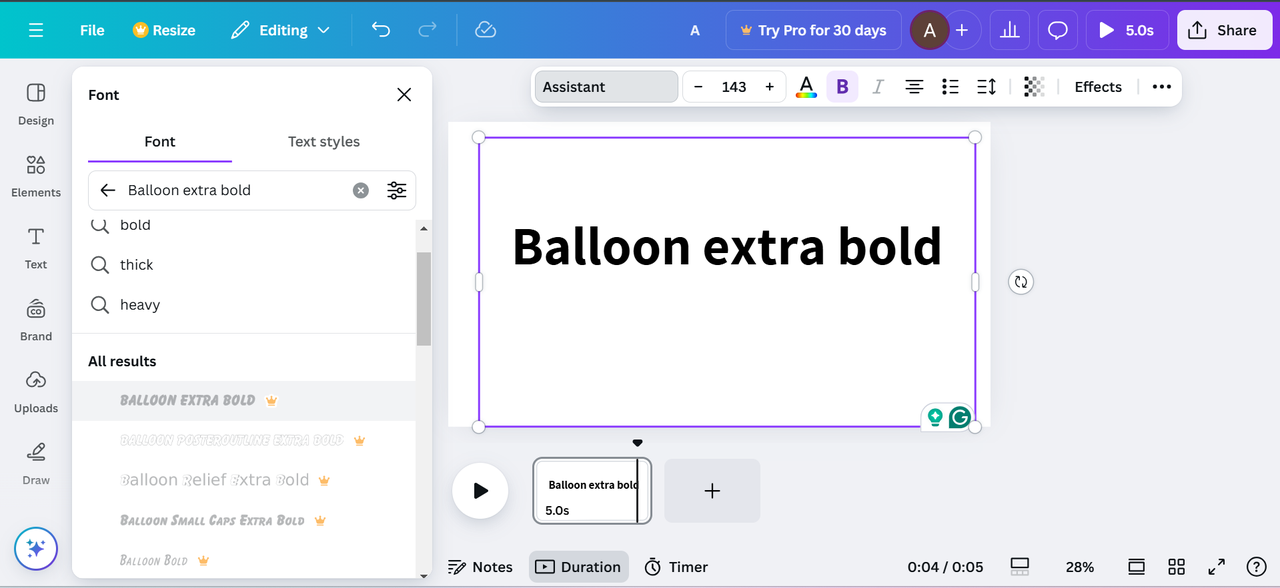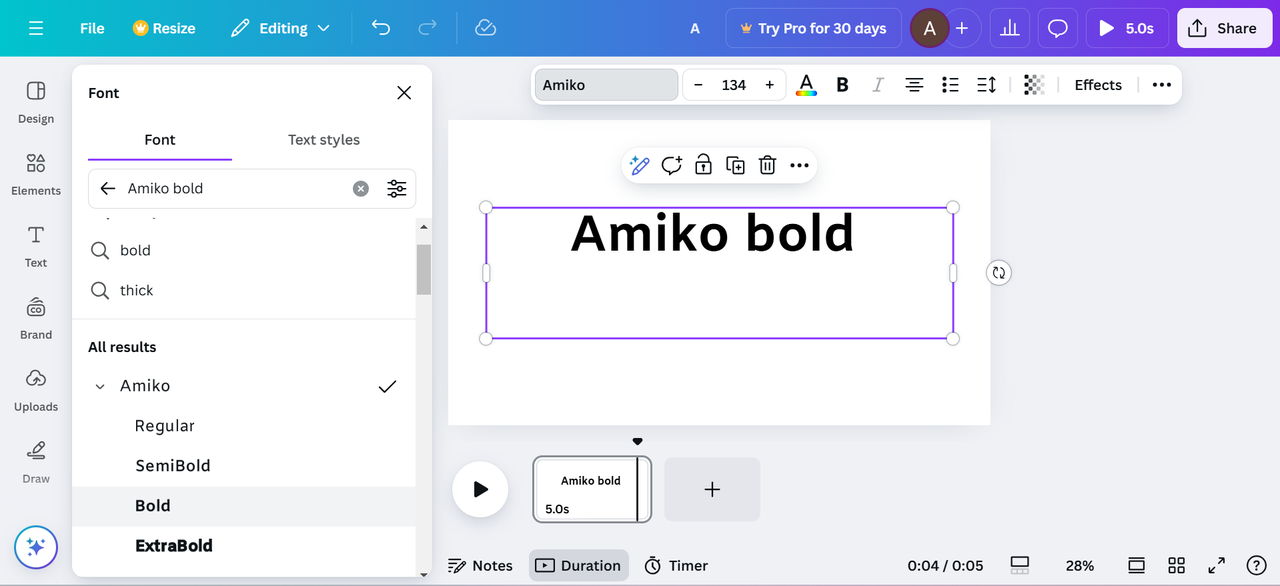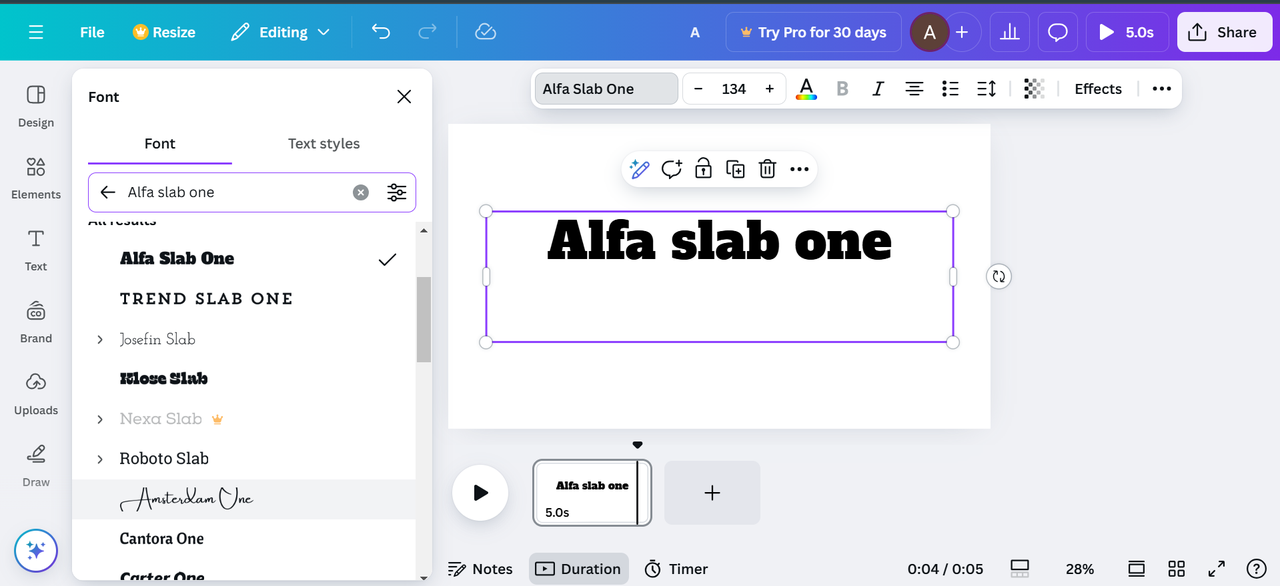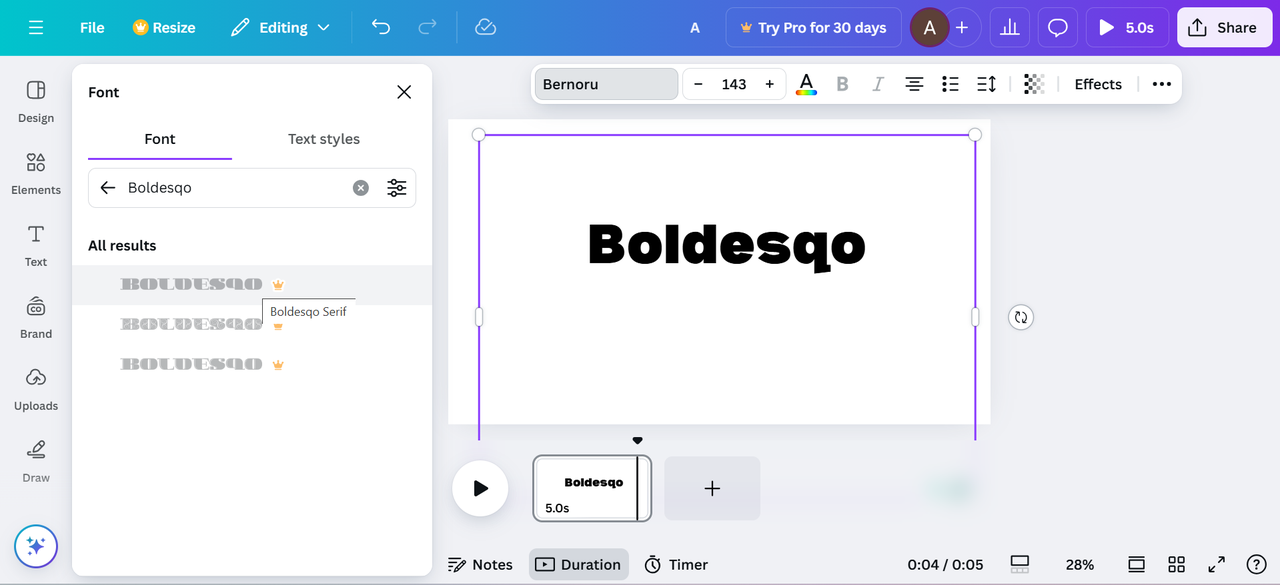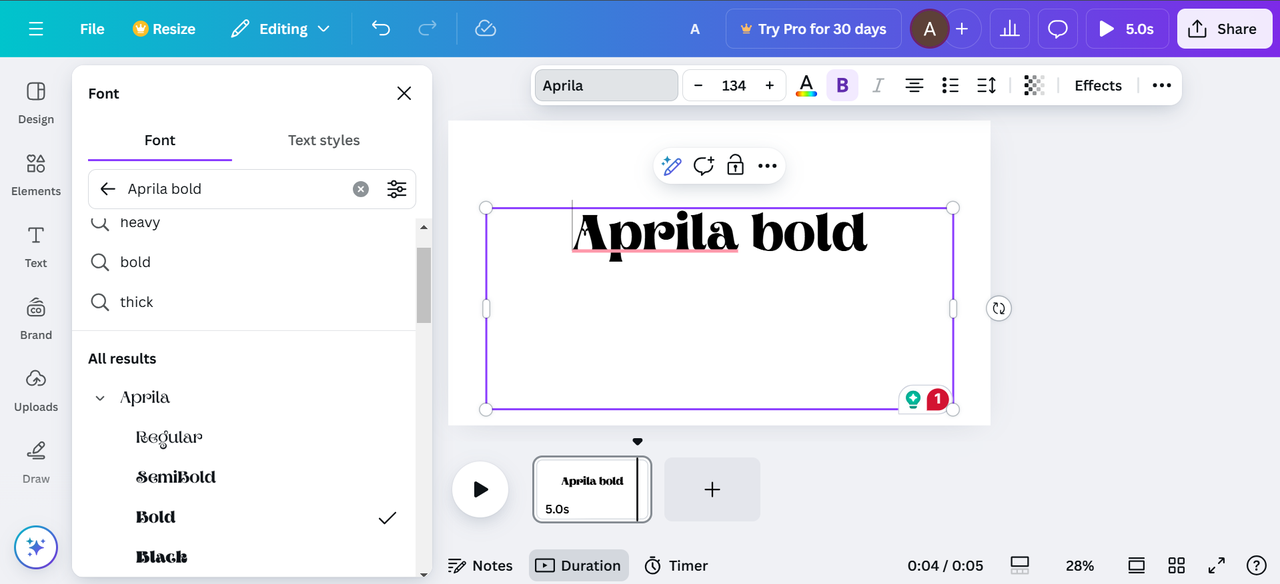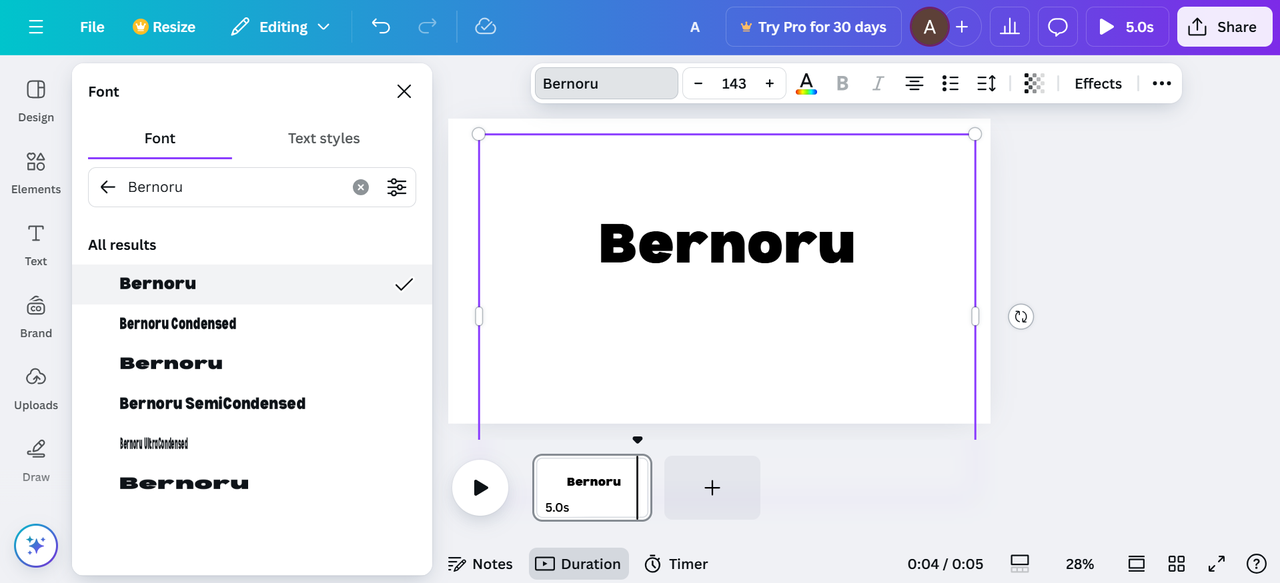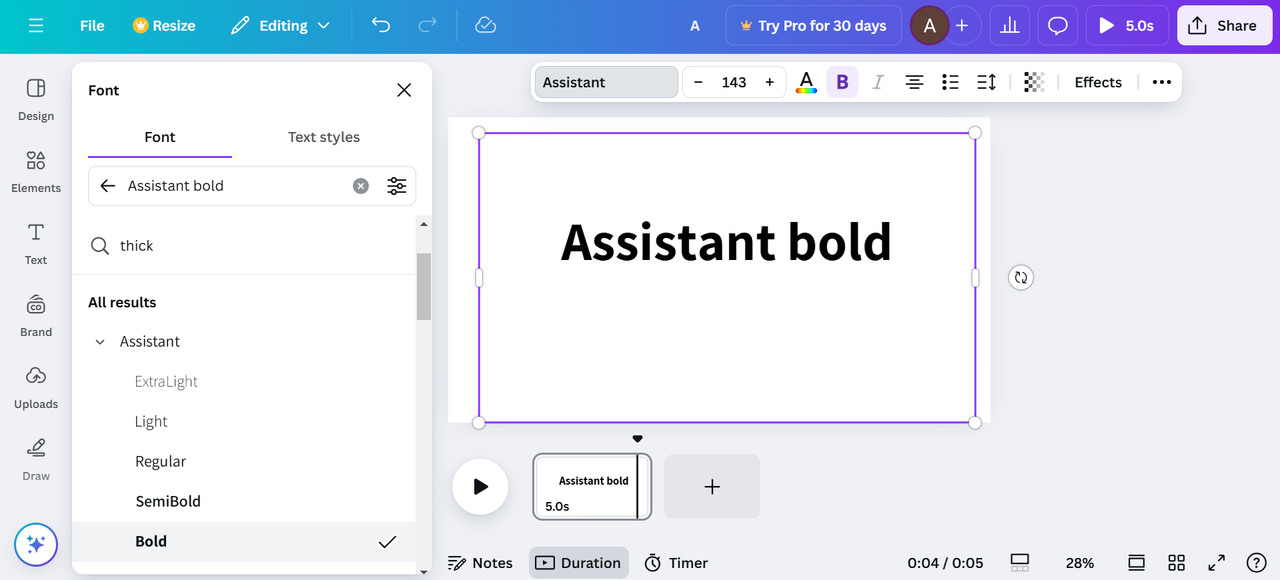
Εξερευνήστε 10 μοναδικές τολμηρές γραμματοσειρές στον Canva για δημιουργικά infographics
Εξερευνήστε τις καλύτερες τολμηρές γραμματοσειρές στο Canva για να κάνετε τα σχέδιά σας να ξεχωρίζουν. Ανυψώστε εύκολα τις αναρτήσεις κοινωνικών μέσων, τις παρουσιάσεις και τα υλικά μάρκετινγκ. Εναλλακτικά, χρησιμοποιήστε τον επεξεργαστή επιφάνειας εργασίας CapCut για να κάνετε έντονη γραφή και να αλλάξετε το μέγεθος του κειμένου σας σε βίντεο.
Το τολμηρό κείμενο είναι ένας ισχυρός τρόπος για να τραβήξετε την προσοχή και να τονίσετε τα βασικά σημεία σε οποιοδήποτε σχεδιασμό, ειδικά στα infographics όπου η σαφής επικοινωνία είναι απαραίτητη. Η Canva, μια ευέλικτη πλατφόρμα σχεδιασμού, παρέχει μια σειρά από μοναδικές, τολμηρές γραμματοσειρές που διευκολύνουν τη δημιουργία εντυπωσιακών οπτικών. Σε αυτό το άρθρο, θα διερευνήσουμε 10 ξεχωριστές τολμηρές γραμματοσειρές στο Canva που είναι ιδανικές για την αποτελεσματική μετάδοση του μηνύματός σας.
Δώστε τολμηρές εντυπώσεις με τις καλύτερες τολμηρές γραμματοσειρές στο Canva
Αν θέλετε το κείμενό σας να αφήσει μια μόνιμη εντύπωση, η επιλογή των τολμηρών γραμματοσειρών της Canva είναι το τέλειο εργαλείο. Από καθαρά, μοντέρνα σχέδια έως κλασικές, τολμηρές γραμματοσειρές serif, η Canva σας βοηθά να δώσετε έμφαση και προσωπικότητα στο κείμενό σας και το καθιστά πηγή για κάθε σχεδιαστή.
Πώς οι τολμηρές γραμματοσειρές στο Canva ενισχύουν τη δημιουργικότητα
Ας ρίξουμε μια πιο προσεκτική ματιά στο πώς αυτή η πλατφόρμα συμβάλλει στις δημιουργικές διατάξεις:
• Βελτιώνει την αναγνωσιμότητα
Οι τολμηρές γραμματοσειρές κάνουν το κείμενο εύκολο να διαβαστεί με μια ματιά και βοηθούν τους θεατές να απορροφήσουν γρήγορα βασικές πληροφορίες, ειδικά σε οπτικά πολύπλοκα σχέδια.
• Ισχυρός οπτικός αντίκτυπος
Οι τολμηρές γραμματοσειρές ξεχωρίζουν σε οποιοδήποτε φόντο, το οποίο προσελκύει την προσοχή αμέσως και προσθέτει ένα στρώμα έμφασης που κρατά τους θεατές αφοσιωμένους.
• Κύρια σημεία
Δίνοντας έμφαση σε κρίσιμες πληροφορίες, οι τολμηρές γραμματοσειρές κατευθύνουν την προσοχή των θεατών στις κύριες ιδέες και καθιστούν τις πληροφορίες σαφείς και πιο αξέχαστες.
• Καινοτόμες διατάξεις
Οι τολμηρές γραμματοσειρές επιτρέπουν δημιουργική διαστρωμάτωση και μοναδικές ρυθμίσεις κειμένου, οι οποίες προσθέτουν ενδιαφέρον και οπτική ιεραρχία στη διάταξη σας.
• Ενισχύει τον οπτικό ρυθμό
Η εναλλαγή των έντονων γραμματοσειρών με άλλα στυλ κειμένου προσθέτει μια ρυθμική ροή στο σχεδιασμό, καθοδηγώντας το μάτι του θεατή ομαλά σε όλη τη σελίδα.
Οι 10 καλύτερες τολμηρές γραμματοσειρές στο Canva για ελκυστικούς τίτλους
Η χρήση τολμηρών γραμματοσειρών στους τίτλους μπορεί να μεταμορφώσει τα σχέδιά σας προσθέτοντας έμφαση, χαρακτήρα και επαγγελματική αφή. Ας εξερευνήσουμε τις κορυφαίες 10 τολμηρές γραμματοσειρές στο Canva για εντυπωσιακούς τίτλους.
1. Τολμηρό οξύ
Το Acid Bold είναι μια σύγχρονη, έντονη γραμματοσειρά με αιχμηρές γραμμές και τολμηρές πινελιές, ιδανική για σχέδια που χρειάζονται μια εντυπωσιακή και αντισυμβατική εμφάνιση. Είναι ιδανικό για καλλιτεχνικά έργα ή διαφημιστικό υλικό όπου θέλετε ένα εντυπωσιακό, σύγχρονο στυλ.
Image showing Acid Bold font in Canva
2. Άλφα πλάκα ένα
Αυτή η πλάκα serif γραμματοσειρά έχει παχιά, blocky γράμματα που προσθέτουν μια ισχυρή, ρετρό αίσθηση σε κάθε τίτλο. Η τολμηρή και δομημένη εμφάνισή του το καθιστά κατάλληλο για αφίσες, διαφημίσεις και branding όπου η αναγνωσιμότητα και ο αντίκτυπος είναι απαραίτητα.
Image showing Alfa slab one font in Canva
3. Μέγεθος Amiko
Το Amiko Bold προσφέρει μια πιο μινιμαλιστική, sans-serif εμφάνιση, συνδυάζοντας την τόλμη με την αναγνωσιμότητα. Είναι ευέλικτο και λειτουργεί καλά για τίτλους σε επαγγελματικές παρουσιάσεις ή ιστοσελίδες όπου η σαφήνεια και η σύγχρονη αισθητική είναι το κλειδί.
Image showing Amiko bold font in Canva
4. Πληκτρολογήστε
Το Aprila bold έχει ένα καθαρό και κομψό στυλ serif που εξισορροπεί την κομψότητα με την τόλμη. Αυτή η γραμματοσειρά είναι μεγάλη για upscale branding, τίτλους περιοδικών ή οποιοδήποτε σχέδιο που χρειάζεται μια πινελιά πολυπλοκότητας μαζί με τον αντίκτυπο.
Image showing Aprila bold font in Canva
5. Βοηθός τολμηρός
Το Assistant Bold είναι μια γραμματοσειρά sans-serif που παρέχει μια απλή, επαγγελματική εμφάνιση. Οι καθαρές γραμμές και το σταθερό βάρος το καθιστούν ιδανικό για εταιρικά υλικά, εκπαιδευτικό περιεχόμενο και ψηφιακά μέσα, όπου απαιτείται ένας απλός αλλά τολμηρός τίτλος.
1. Γιατί οι γραμματοσειρές Canva χρησιμοποιούνται σε περιεχόμενο βίντεο;
Οι τολμηρές γραμματοσειρές Canva είναι δημοφιλείς στο περιεχόμενο βίντεο επειδή παρέχουν υψηλή αναγνωσιμότητα και προσελκύουν γρήγορα την προσοχή, ακόμη και σε μικρότερες οθόνες. Οι ισχυρές και καθορισμένες γραμμές τους τις καθιστούν ιδανικές για τη δημιουργία αξέχαστων τίτλων, λεζάντες ή προσκλήσεις για δράση που οι θεατές μπορούν εύκολα να ακολουθήσουν σε γρήγορα μέσα. Εκτός από το Canva, ο επεξεργαστής βίντεο για επιτραπέζιους υπολογιστές CapCut είναι ένα άλλο εξαιρετικό εργαλείο για την προσθήκη τολμηρών γραμματοσειρών σε βίντεο.